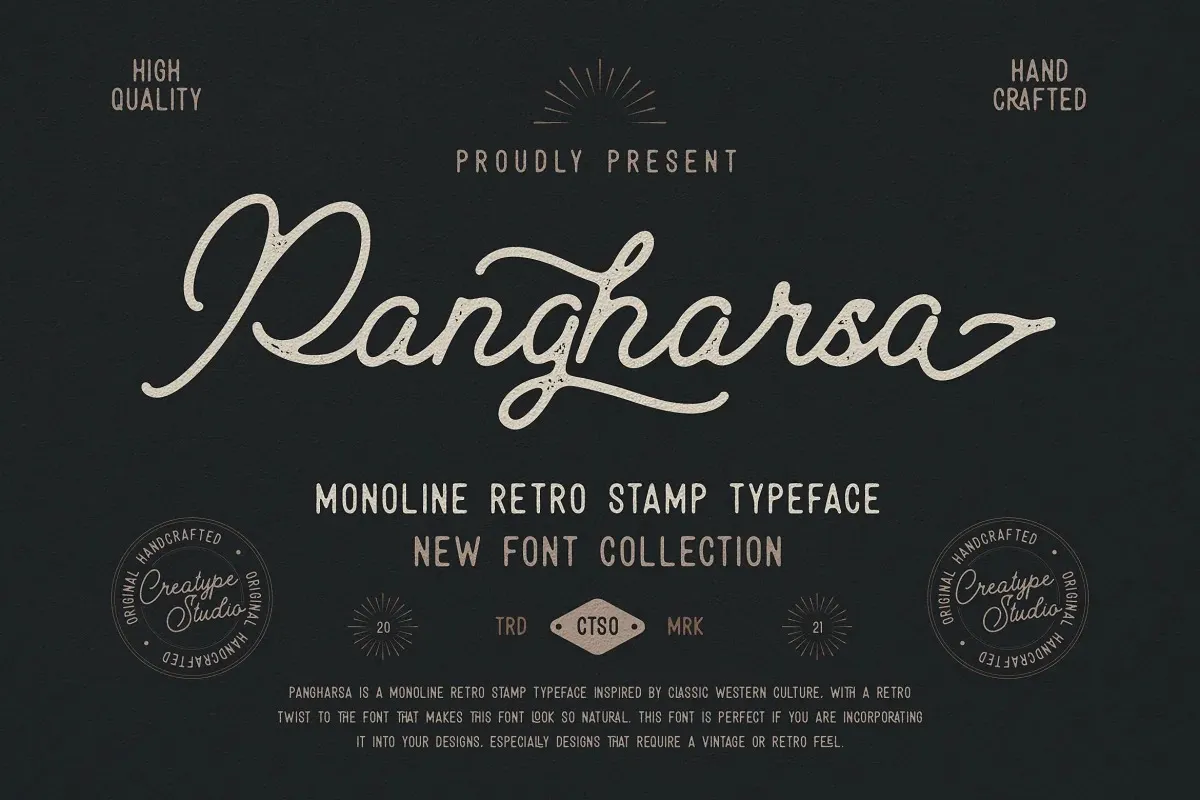
Pangharsa Font – Download Grátis
A “Pangharsa Font” é uma elegante escolha para qualquer designer que busca trazer um toque vintage aos seus projetos digitais. Este script monoline é resultado de desenho a mão, mantendo ao mesmo tempo um ar sofisticado. Seja em seu projeto profissional ou em um momento retro, essa fonte oferece uma aparência elegante e contemporânea sem comprometer a originalidade do design. É perfeito para aqueles que querem incorporar um aspecto vintage sem desvirtuar o resultado final. Ideal para projetos gráficos antigos ou vintage, seja para uma publicação de revista ou qualquer outro trabalho de arte digital que exija um ar nostálgico, a “Pangharsa Font” traz a riqueza e versatilidade necessária para expressar sua identidade visual.